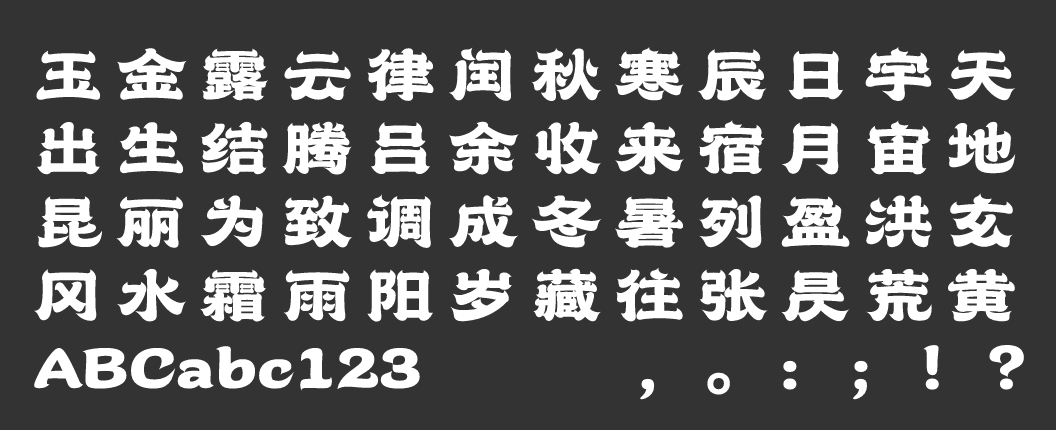
汉仪赤云隶 W
汉仪赤云隶 | 赤云隶变,气贯今古
“汉仪赤云隶”是由知名设计师行行珂与汉仪字库合作打造的一款带有隶书韵味的设计字体。这款字体运用现代设计语言,在隶书的基础上改造创新,给予了传统字体新的生命力。它曾入选:Award360°年度设计100、《第十四届亚太设计年鉴》、《Design 360°n.84 #特刊#》和《字赋不凡2》 ,是一款广泛适用于国风风潮环境的优质标题字体。
汉仪赤云隶 | 字体古中带新
“汉仪赤云隶”是以隶书为原型进而演变创作,字形略带篆意,古中带新。
“汉仪赤云隶”采用了隶书的结构,字体宽扁,重心一致,字取横势,给人一种稳定、厚重的感觉。
汉仪赤云隶 | 笔画张扬外放
“汉仪赤云隶” 在古隶书温润的基础上融入张扬外放的笔触,在起、收笔处的笔画设计上强化了笔锋造型,具有一定装饰性,如同燃烧的火苗一样,在这个年轻的时代迸发出独特的张力和韵味。
汉仪赤云隶 | 曲线饱满灵活
“汉仪赤云隶”的笔画浑厚有力、气势宏大,行笔流畅有力度,线条饱满有弹性,表现出了其生动活泼的特点。
“汉仪赤云隶”的笔画在字体不同的位置有不同的状态及表达。以“捺”笔画为例,按字形特点共分为“短捺”、“斜捺”和“平捺”。“短捺”的捺身较短促;“斜捺”头细尾粗,比较陡峭;“平捺”则一波三折,形似波浪。
汉仪赤云隶 | 中西文匹配
“汉仪赤云隶”的西文既留有传统英文书法的结构又参照了中文笔画的特点。这使得汉仪赤云隶的中西文在历史文化和现代设计上都有着极高的匹配度。
汉仪赤云隶 | 西文排版展示
汉仪赤云隶 | 应用展示
中文监制
李晓静
中文设计执行团队
汉仪字研工作室
西文设计
霍悦昕